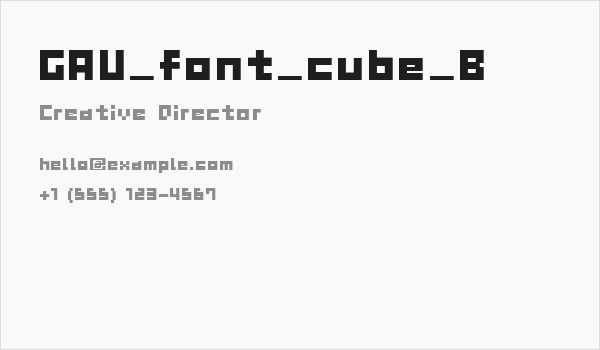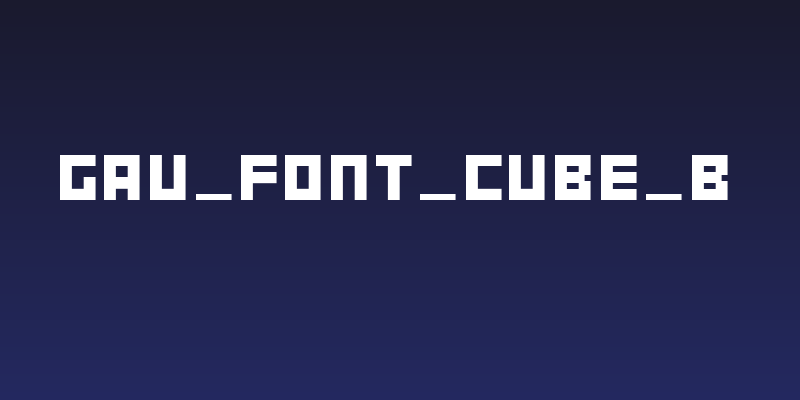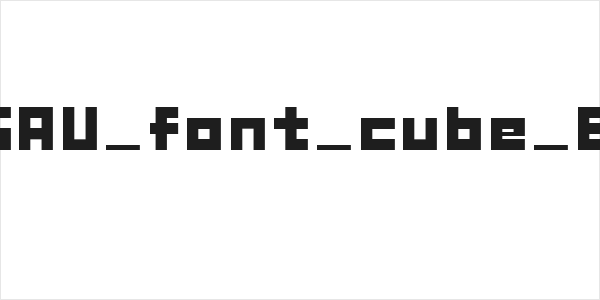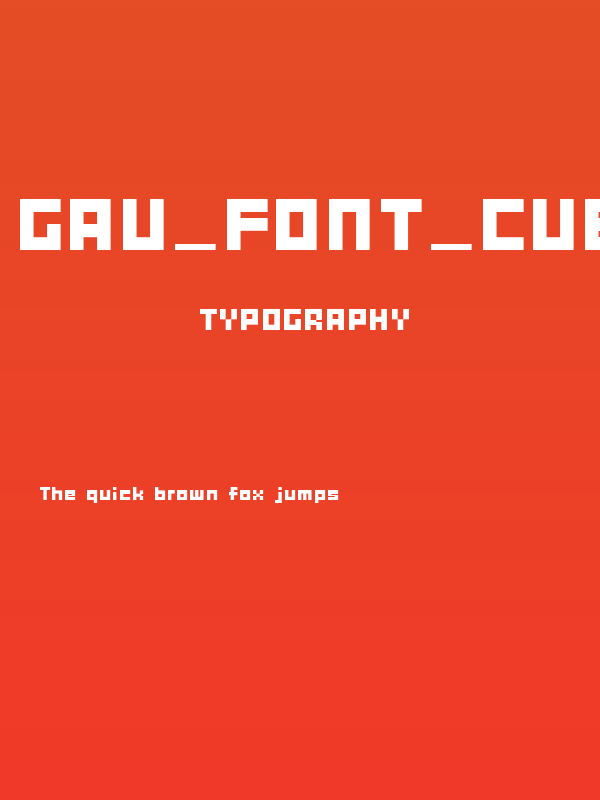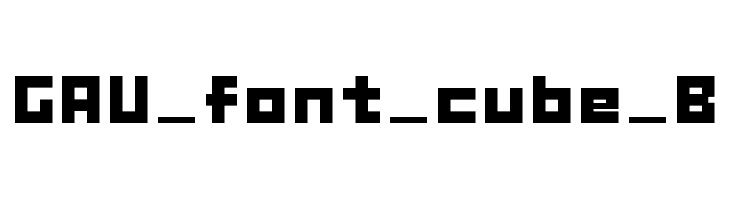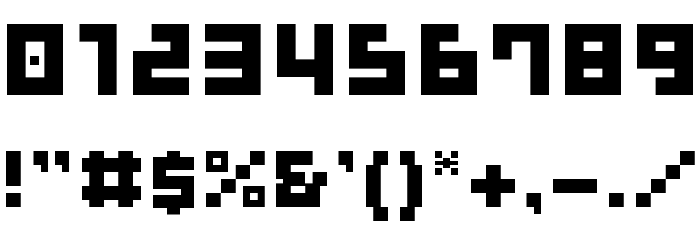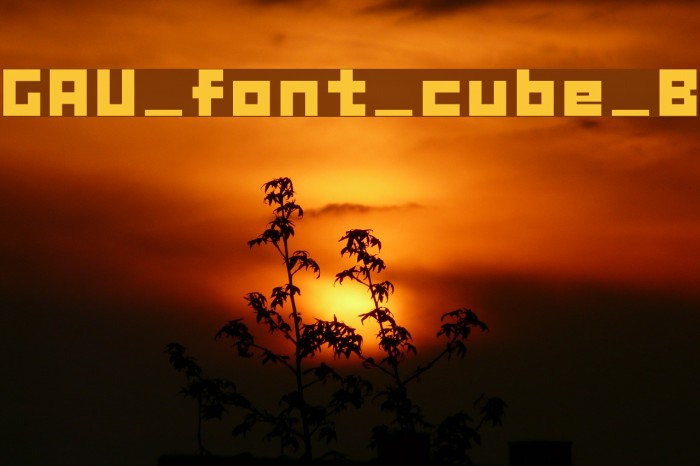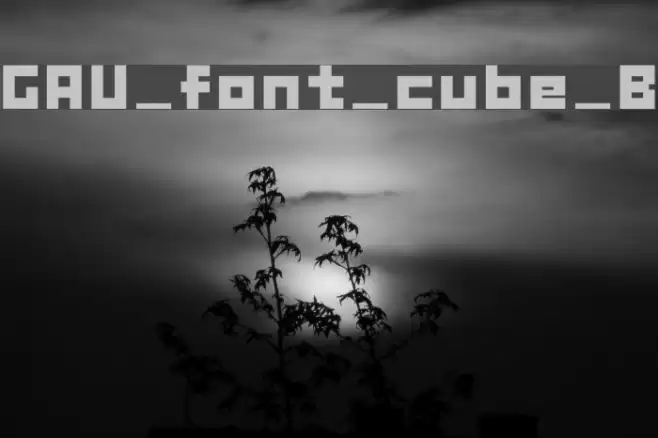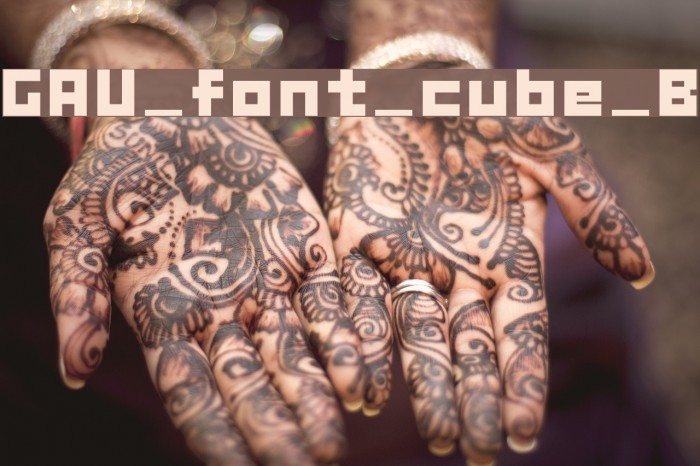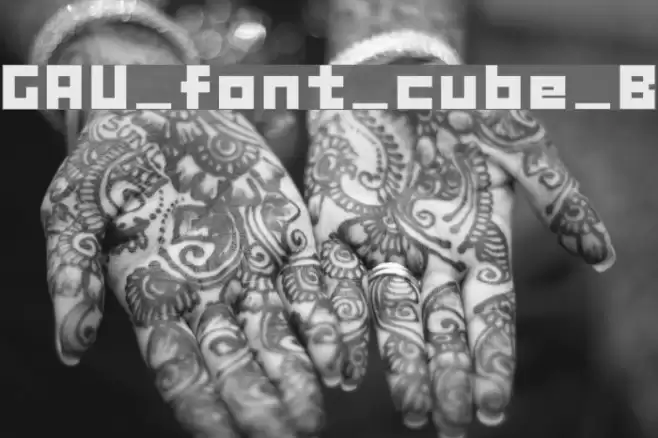
GAU_font_cube_B Font
| Estilo geral | Retro, Digital |
| Projetos propostos | Ideal for video game designs, digital art projects, retro-themed posters, and tech-related branding. |